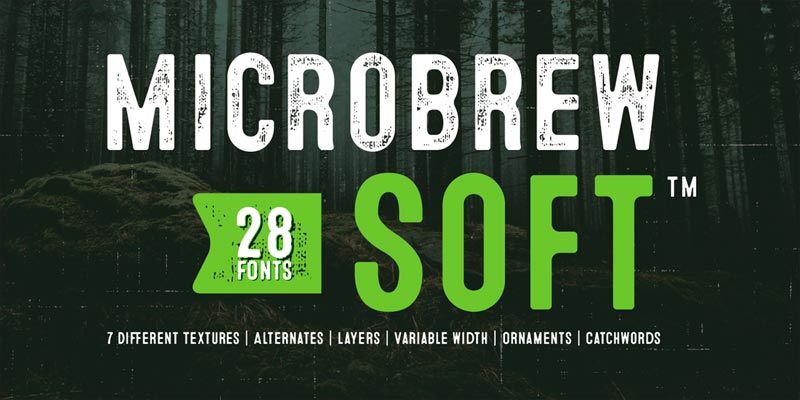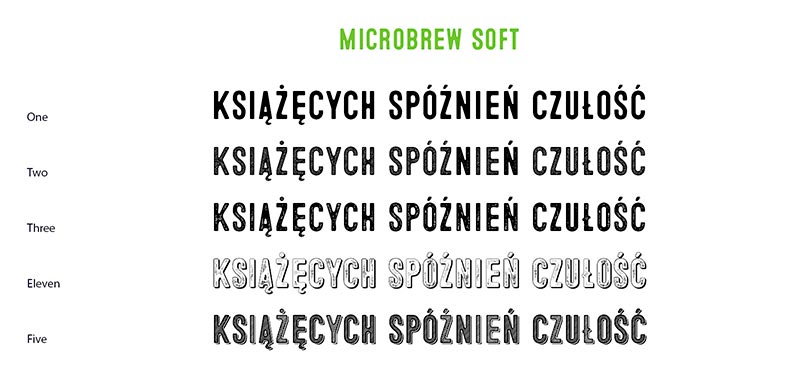
Font Microbrew Soft
Do naszego studia trafił zestaw fontów Microbrew Soft, składający się z 28 odmian. Dzięki charakterowi retro, font nadaje się szczególnie do projektów opakowań żywności oraz tematów związanych z ekologią i tradycją.